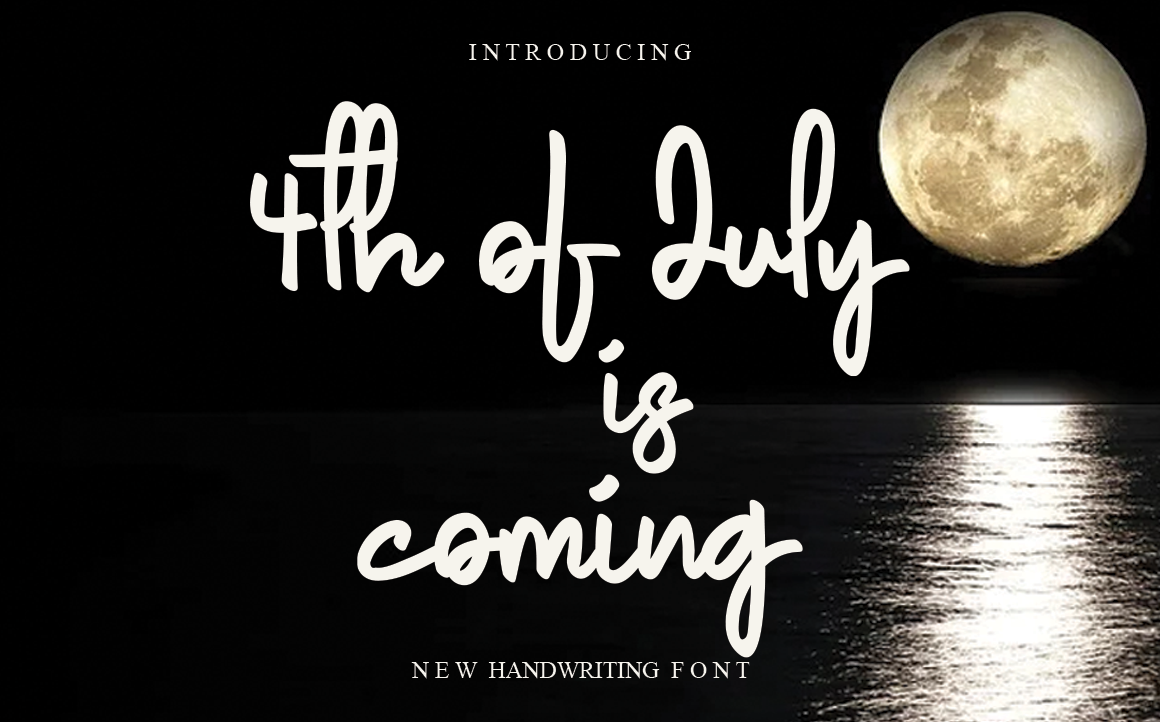
4th Of July Is Coming Font – Download Grátis
Essa fonte é perfeita para quem busca adicionar um toque especial a suas criações digitais e físicas. Esta é uma fonte handwritten única e leve que combina simplicidade com criatividade, ideal tanto para Instagram Stories quanto para projetos de gráfica DIY. Se você está buscando dar vida a ideias inovadoras em sua próxima publicação ou projeto, este será o recurso perfeito. Com esse design elegante e descontraído, qualquer conceito poderá ser transformado num verdadeiro trabalho de arte. Ideal para quem busca um toque diferenciado sem comprometer a simplicidade e a facilidade de uso da fonte. Seja você um fotógrafo criando stories personalizadas ou uma designer decorativa adaptando designs existentes, esta é sua escolha perfeita.